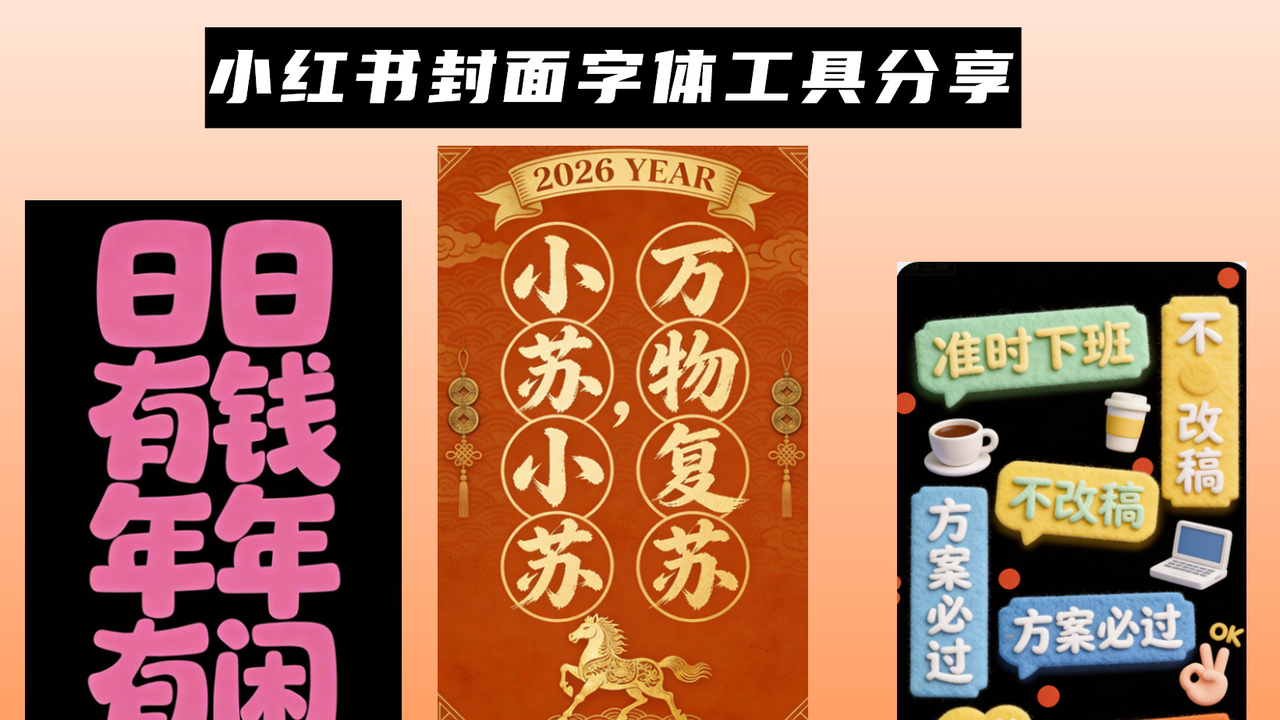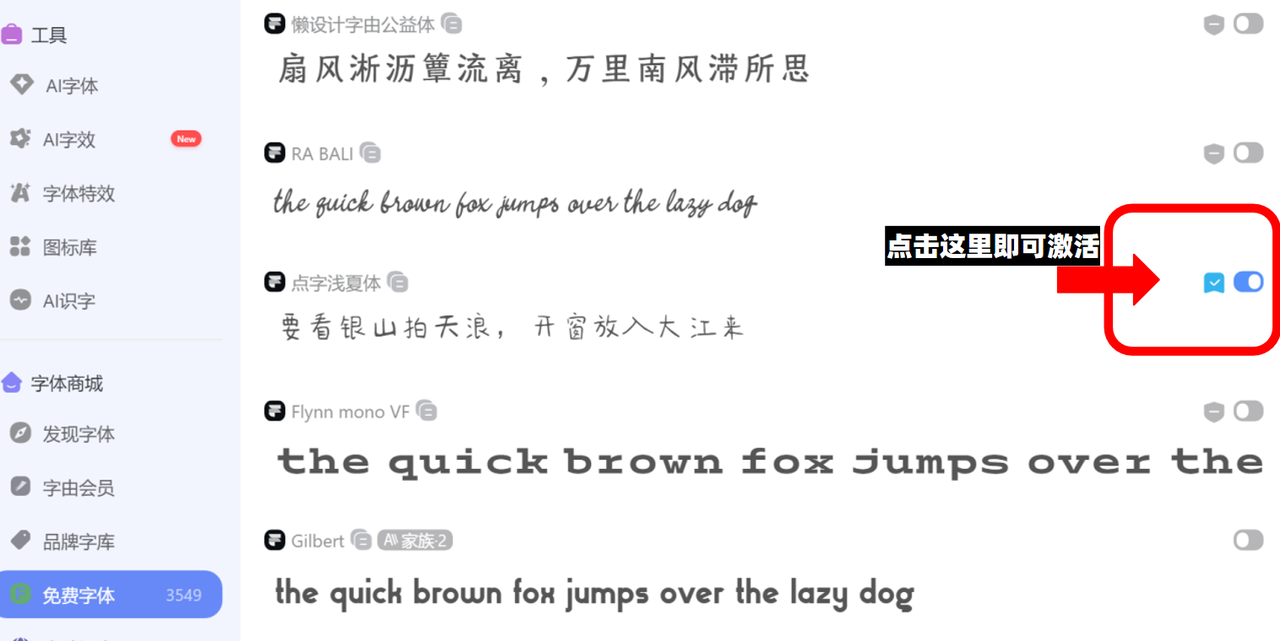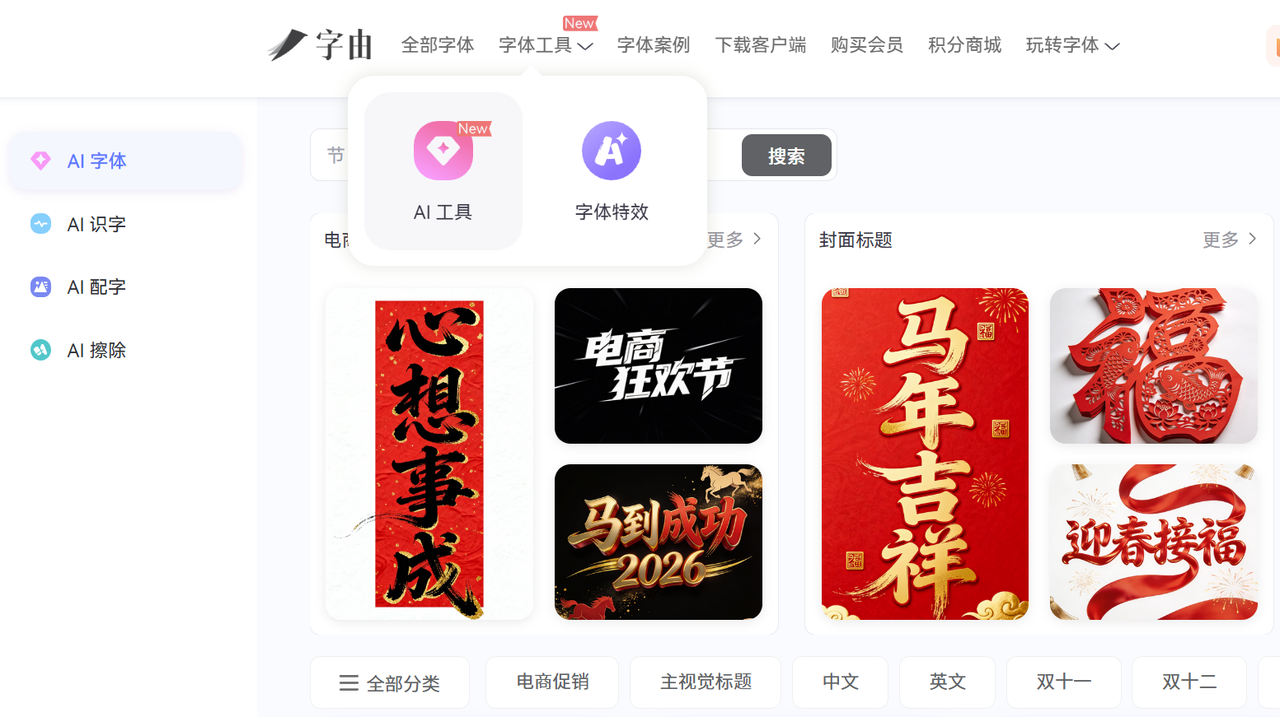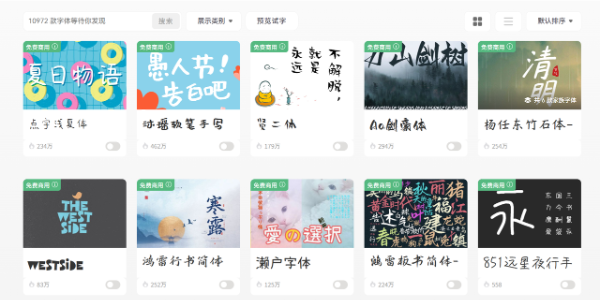
打造吸睛的小红书封面字体,新手也能拿捏
做过小红书的都懂,封面就是笔记的“流量敲门砖”!用户划屏速度快到离谱,平均3秒就划走一篇,要是封面字体平平无奇、没一点记忆点,哪怕内容再干货,也没人愿意点进来。我当初也纠结过要不要学PS、买付费字体,后来发现根本没必要——选对工具,新手也能轻松做出适配赛道、自带吸睛感的小红书封面字体。今天就把我私藏的4款工具分享给大家,全是亲测好用、上手无压力的。接下来本文先以字由网的“AI字体”,也是我日常用得最的工具来教大家打造小红书封面字体!
字由网
字由网绝对是新手首选字体工具,我当初刚做小红书时,第一款字体工具就用的它。大家可以选择两种方法制作小红书封面字体。我先为大家介绍第一种,直接挑选字由网的字体。它的风格分类特别细,小红书上热门的手写风、复古风、卡通风、极简风全都有,不用反复调试,总能找到适配自己笔记赛道的字体。
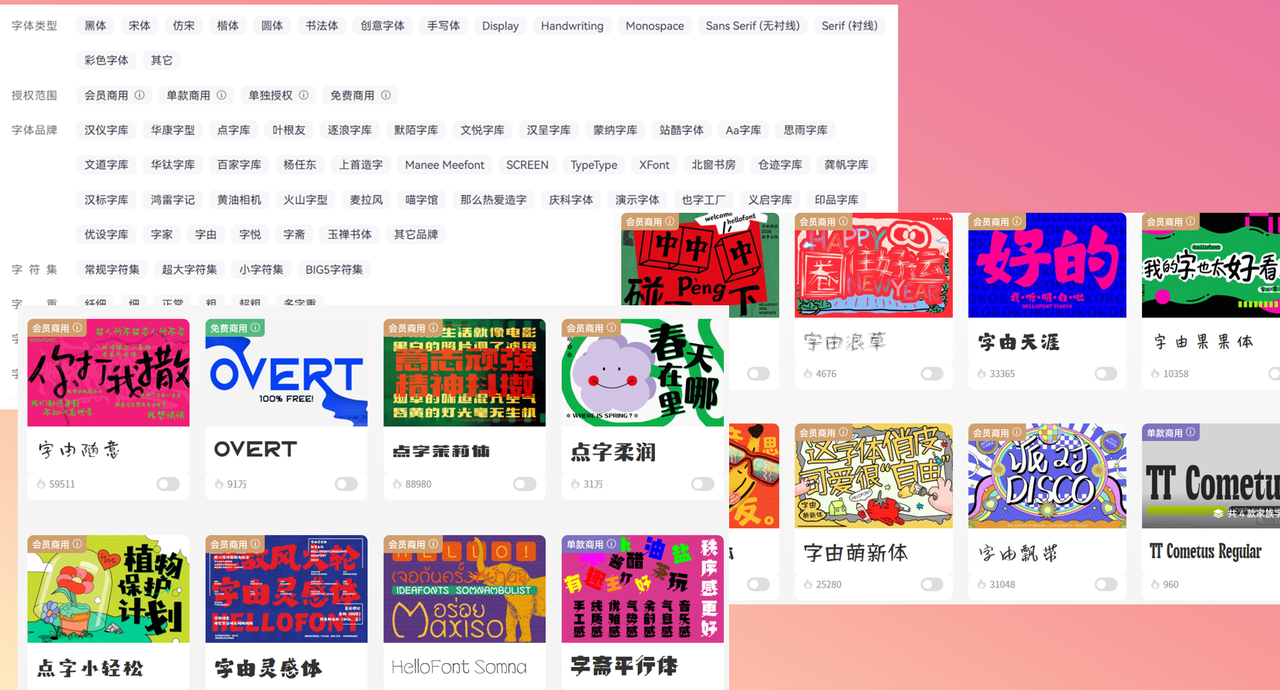
第二种方法就是用字由的「AI字体」功能,首先打开字由网在首页顶端菜单栏中找到AI工具,利用AI字体快速生成小红书封面字体。字由提供的字体模板风格非常丰富,大家可以通过筛选风格类型,快速定位到自己想用的字体。
找到喜欢的字体模板后,点击模板上的做同款就能打开字体模板页面。
这里有个小tip:小红书封面字体要与字体模板字数一致喔,超出的字体会输入不了~
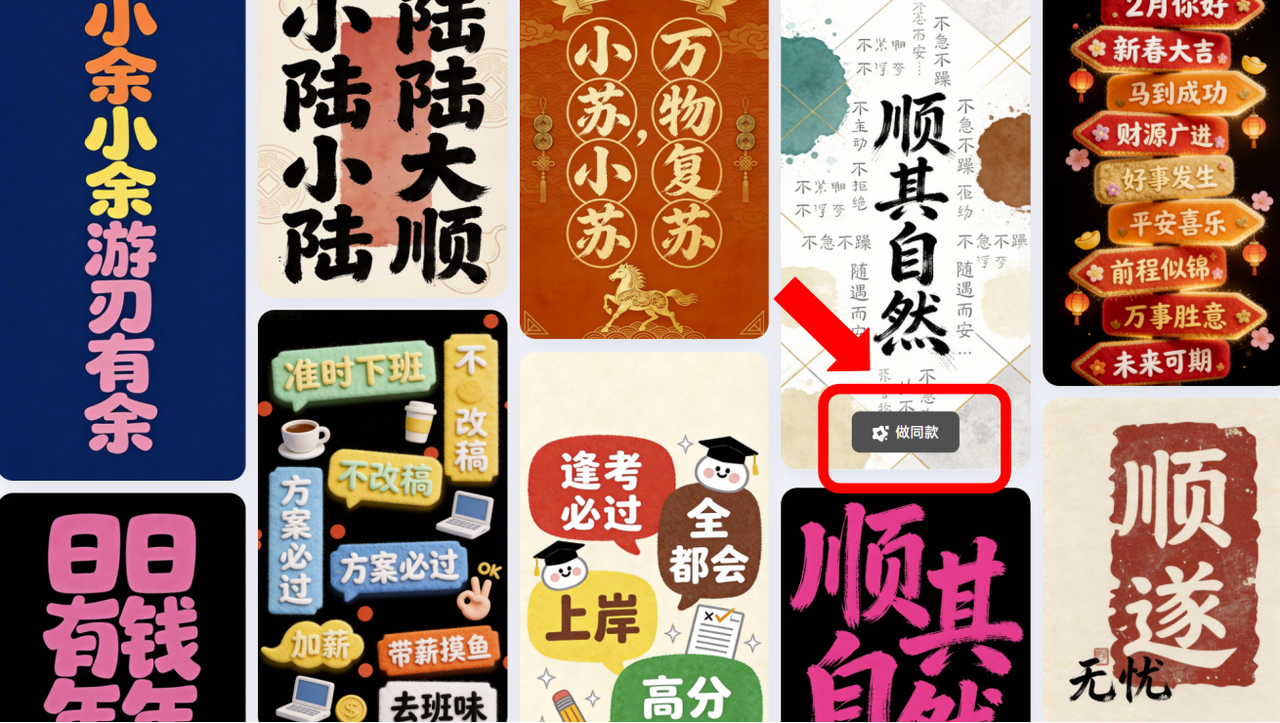
输入你想做的封面文案(比如“美妆好物合集”“职场干货分享”),筛选对应风格模板后点击生成,就能拿到高清字体。
当然字由还有最戳我的是它的AI字体识别功能,刷到别人的小红书爆款封面字体,不知道字体名字也没关系,上传图片就能识别,直接套用同款风格,省了超多找字体的时间。
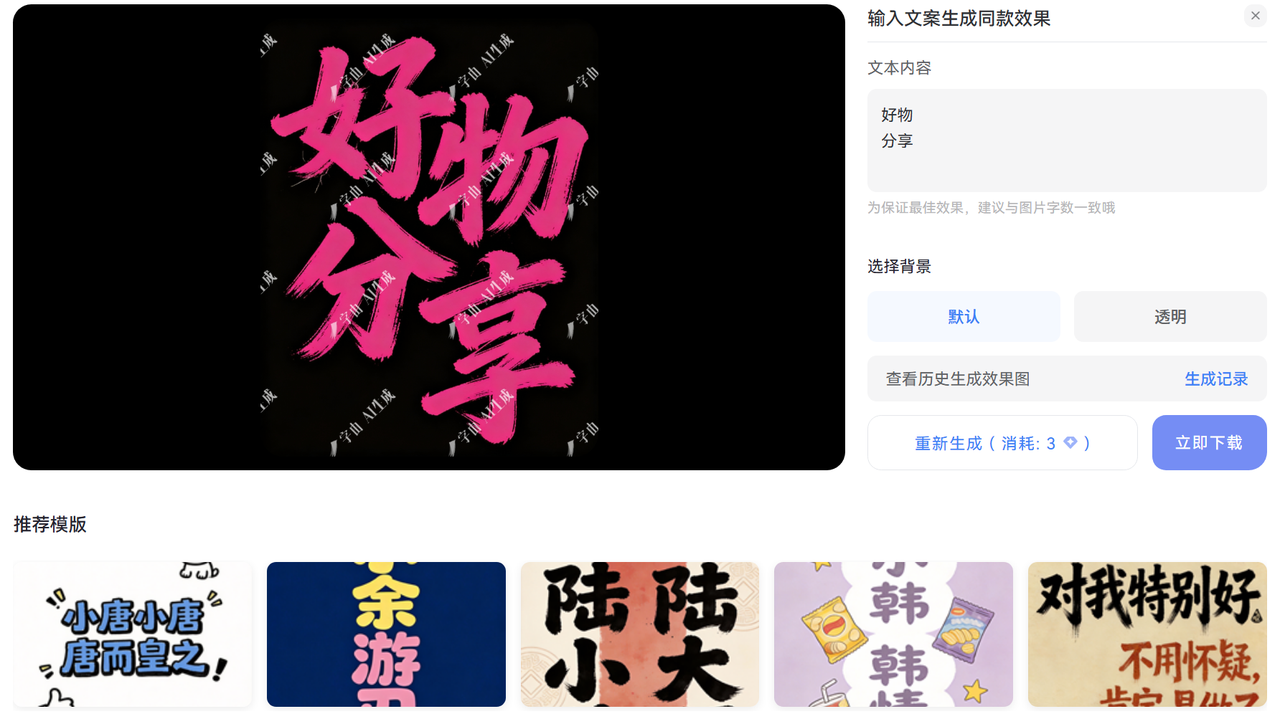
Adobe Illustrator
很多新手一听到Adobe Illustrator(简称AI),就觉得是专业设计师才会用的软件,不敢尝试,但其实它的字体创作功能,新手稍微摸索下就能上手,做出来的字体质感,是普通在线工具比不了的,想让封面摆脱同质化、更有高级感的可以试试。我教大家一个简单的实操步骤:新建一个适配小红书封面尺寸的文档,用文字工具输入文案,选一款基础字体,然后通过顶部“效果”菜单,添加变形、描边、渐变或者立体特效,还能用水滴编辑功能优化字体线条,做出专属的小红书封面字体。
Canva
Canva应该是很多博主都在用的在线设计平台,我平时批量做小红书封面时,用它也很多,兼顾新手友好度和商用安全性,不用额外找小红书封面字体素材,足够新手用了。它最贴心的就是能兼顾字体生成和封面设计,彻底解决新手“字体难选、排版难搞”的问题,全球很多小红书等自媒体博主都在靠它高效出图,实用性拉满。
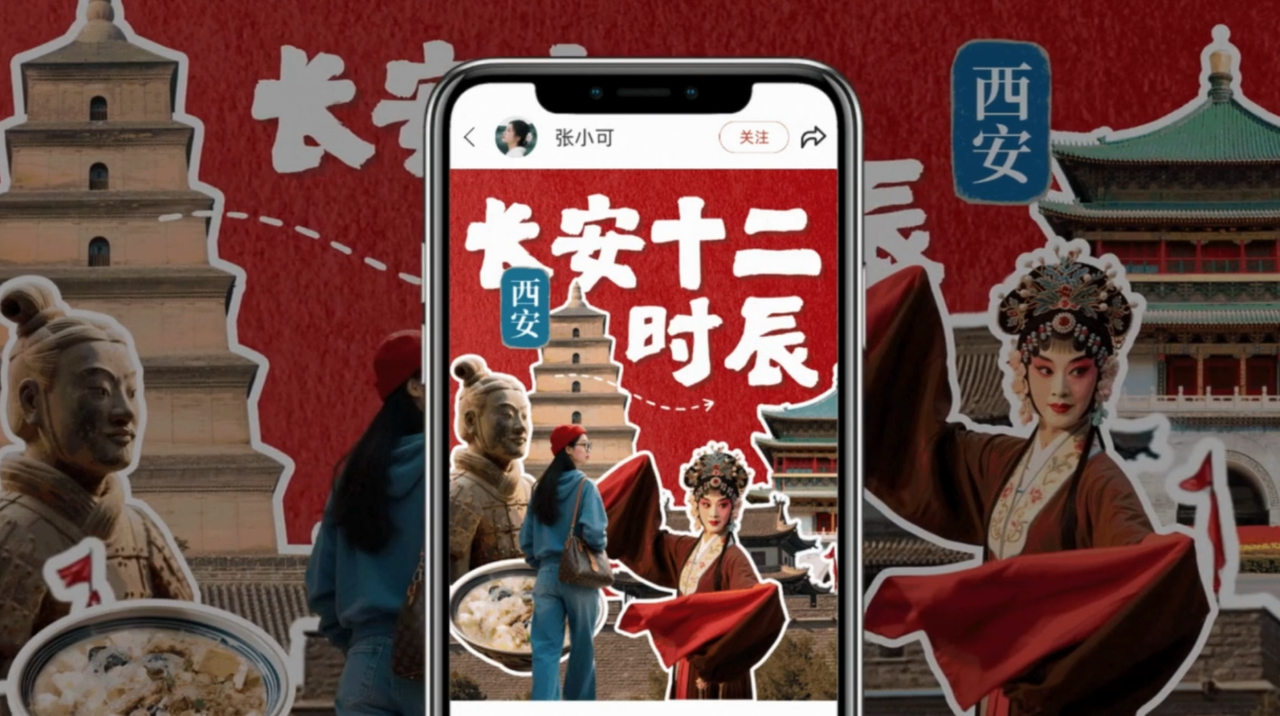
四、创客贴:模板联动,字体+封面一站式搞定
创客贴是我私藏的全能设计工具,主打零门槛操作,特别适合不想来回切换工具的新手,它不只是能生成小红书封面字体,还能直接搭配封面模板,完成一站式设计,不用单独做字体再拼封面,高效又省心。小红书上热门的风格全都覆盖,软萌卡通体、简约黑体、文艺行书、复古宋体应有尽有,兼顾实用性和颜值,而且不用担心版权问题,商用也靠谱。
其实做小红书封面字体,核心根本不是搞复杂设计,选对和自己赛道匹配的工具,不用花太多时间,就能拿捏封面流量密码。以上4款工具都是我亲测好用的,各有侧重,新手可以按需选。
最后给新手避几个我当初踩过的坑:封面字体最多用2种,多了会显得杂乱,反而拉低质感;文字和背景一定要有足够的对比度,不然看不清,等于白做;优先用免费商用字体,别随便用付费字体,避免侵权踩坑。这4款工具都能满足需求,不用花大量时间学设计,3分钟就能做出吸睛封面,助力笔记突破流量瓶颈,不管做什么品类、什么风格的笔记都能用,让每一篇优质内容都能被更多人看到。